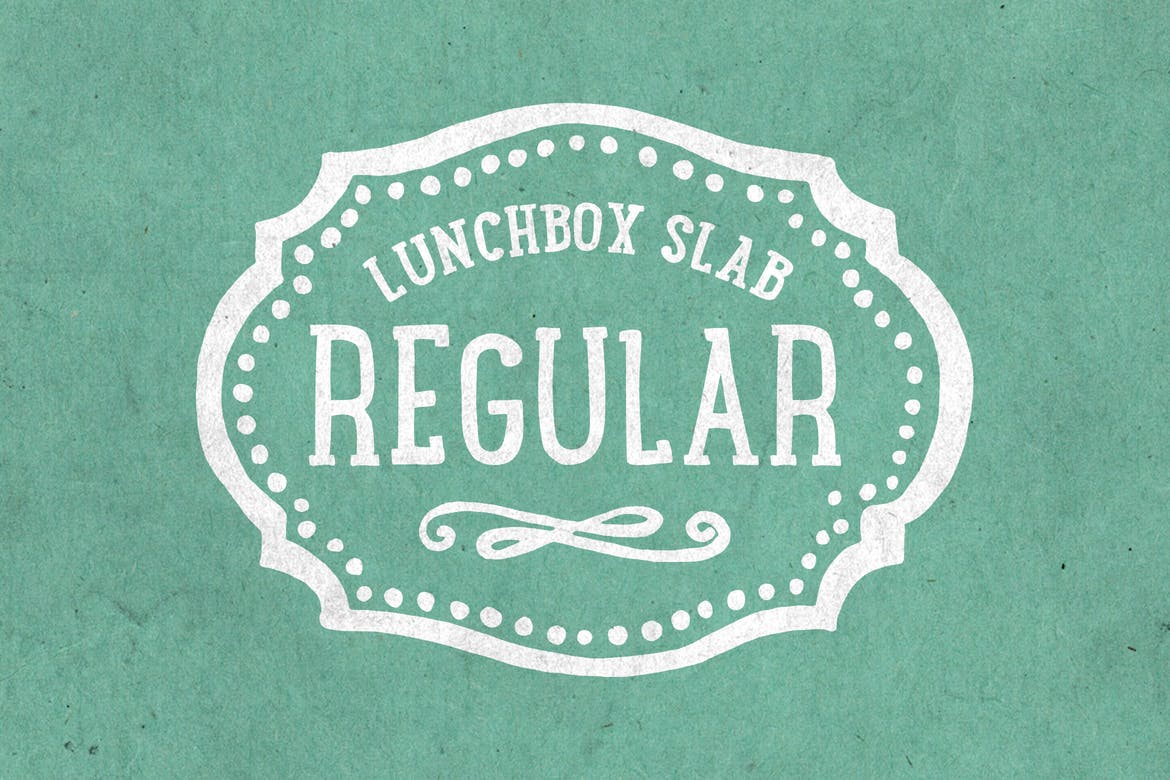
デザインにぴったり合うフォントを見つけるのに苦労しているデザイナーの皆さん、いい記事に出会いましたね!クオリティの高いフォントを探すのには手間がかかることは十分承知ですので、そんな皆さんのために代わりに探してきました。100種類以上の無料フォントがあるので、きっと探していたものが何種類かは見つかるはずです。まさに探していたフォントが見つかることでしょう!
すっきりはっきりとしたフォントを重点的に集めたので、webであれ印刷物であれデザインにプロフェッショナルな感じや読みやすさを与えてくれるでしょう。以前に手書き風フォントや、ブラシ風フォント、SF風フォント、立体的なフォント、ゴシック調のフォント、それからクリエイティブで風変わりなフォントはすべて紹介してしまったので、今回はあまり装飾過多な物は紹介しません。
フォントの種類に頭を悩ませることなく、探していたフォントを手早く見つけられるように、フォントをカテゴリ別に分けました。カテゴリはセリフ体、サンセリフ体、スラブセリフ体、モノスペースに分かれています。
無料のセリフ体フォント
セリフ体の特徴は文字や数字の端に小さな線(装飾)が付いていることです。セリフ体のフォントは読みやすいとされており、文字がはっきりしていて認識しやすいため、印刷物などで一般的に使われます。
後々紹介するスラブセリフと同様、例外はあります。セリフ体には、以下のリストにもあるように、webサイトのタイトルや見出しに使えるものが多いですが、本文テキストにも使えるものもあります。くれぐれも、webサイトに使うフォントは慎重に選んでください。
Bitter HT Serif
Bitter HT Serifには通常書体、イタリック、太字、太字イタリックが含まれています。Sol Matasさんによるデザインです。
Arkibal Serif(Envato Elementsへの登録が必要)
Arkibal SerifはJan-Christian Bruunのデザインによる6種類のスタイルの現代的なセリフ体フォントです。
PT Serif
PT Serifには通常書体、太字、イタリック、太字イタリックがあります。ParaTypeによるデザインです。
Ayres Serif
Ayres Serifには合字や代替文字が含まれます。Mariel Gornatiさんによるデザインです。
Magnifika(Envato Elementsへの登録が必要)
Magnifikaは古風な小文字のレタリングに着想を得た、ビクトリア朝風のフォントです。画面上でも映えますが、印刷物にも使えます。
Rhytmic Dances(Envato Elementsの登録が必要)
Calendas Plus Serif Font Family
Calendas Plus Regularにはデスクトップとwebフォントがあります。Altipo Fontsによるデザインです。
Kula(Envato Elementsの登録が必要)
Kulaは面白い曲線のあるフォントです。微妙ではありますが、力強いフォントです。4種類のフォントは、ポスターやスライドショーのタイトルや見出しといった派手で直接的な宣伝に使えます。
SilverLeaf Handwritten Serif
SilverLeafは手書きのセリフフォントでデスクトップとwebフォントがあります。Nathan Brownさんのデザインです。
YoungSerif Medium Typeface
YoungSerif Mediumにはデスクトップとwebフォントがあります。Uplaodによるデザインです。
Pratiwi Typeface(Envato Elementsの登録が必要)
デザインに本格的な手書き感を与えます。Pratiwi Typefaceは文房具やロゴに最適です。
Droid Serif
Droid Serifには通常書体、太字、イタリック、太字イタリックがあります。Steve Mattesonさんのデザインです。
Foundry – font pack(Envato Elementsの登録が必要)
このリストのなかでもケーニングの出来がかなり良い手書きフォントです。TTF、WOFF+OTFの両形式があります。
Jura Serif Typeface
Jura Serifには通常書体、太字、イタリック、太字イタリックがあります。Ten by Twentyによるデザインです。
Merriweather Serif
Merriweatherには通常書体、ライト、太字、イタリック、ブラックがあります。Eben Sorkinさんのデザインです。
Rumble Brave Vintage Fonts(Envato Elementsの登録が必要)
Rumble Braveはビクトリア朝風のクラシックなフォントで、曲がりやうねりが気取ったディスプレイ用のフォントです。パッケージには8種類のスタイルが含まれています。
Vollkorn Serif
Vollkorn Serifには、通常書体、太字、イタリック、太字イタリック、セミボールド、セミボールドイタリック、ミディアム、ミディアムイタリックがあります。Friedrich Althausenさんのデザインです。
Appareo Extras(Envato Elementsの登録が必要)
古書のページをイメージしたAppareoは不完全で欠けた3種類のスタイルのフォントです。
The Crimson Text Typeface
The Crimson Text Typefaceには太字、太字イタリック、イタリック、ローマン、セミボールド、セミボールドイタリックがあります。Sebastian Koschさんのデザインです。
Calluna Serif
Callunaにはライト、通常、イタリック、セミボールドイタリック、太字イタリック、ブラックの書体があります。exljbris Font Foundryによるデザインです。
Mon Cheri Typeface + Extras(Envato Elementsの登録が必要)
Mon Cheri typefaceはサンキューレターに最適です。気持ちのこもったデザインで、ユニークなOTFフォントが2種類あります。